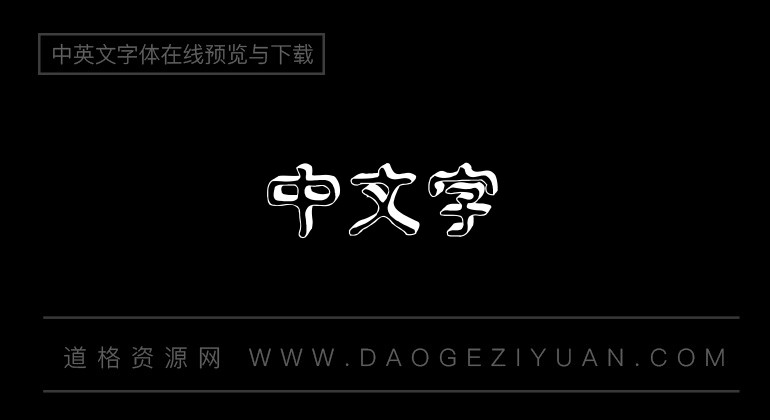
金梅古印立体国际码
金梅古印立体国际码字体是一种专为网页设计而设计的字体,它在汉字书写方面具有独特的优势。它采用了立体国际码,可以使文字更加立体生动,更加美观大方,画面更加精细,更加清晰。它还拥有优秀的拉伸性,可以根据不同的网页设计需求,调整字体的大小,以适应不同的屏幕大小。
金梅古印立体国际码是一款非常不错的手写艺术字体,具有很好的视觉感,适合于文化类的宣传设计、商业类品牌的广告和产品包装设计以及个性化文字排版等较多场景。